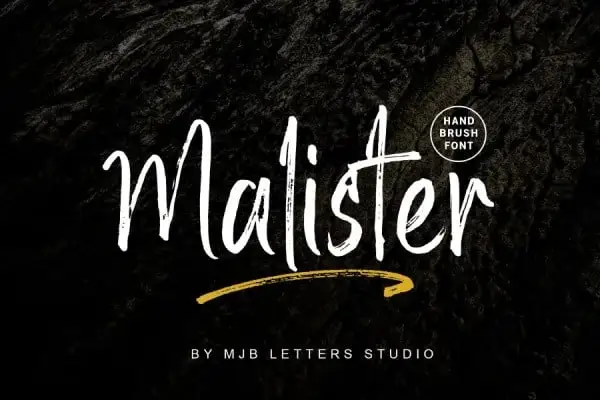
Malister Brush Font – Download Grátis
A fonte Malister Brush é uma escolha perfeita para quem deseja dar vida a suas criações com um toque casual e exuberante. Desenvolvida por meio do uso de um chicote desbotado, esta tipografia é uma verdadeira expressão da arte manual. Criada pelo designer font MJB Letters, a Malister Brush oferece uma textura firmemente robusta, criando um impacto irresistível em qualquer design ao qual seja aplicada. Perfeita para uma variedade de usos, desde logomarcas e flyers até revistas e cartões de visitas, esta fonte é perfeitamente adaptável aos mais diversos ambientes. Seja você um designer gráfico ou criativo que busca dar vida à sua arte com o toque justo do design, a Malister Brush oferece precisão e expressividade, tornando-a uma escolha inspiradora para qualquer projeto.